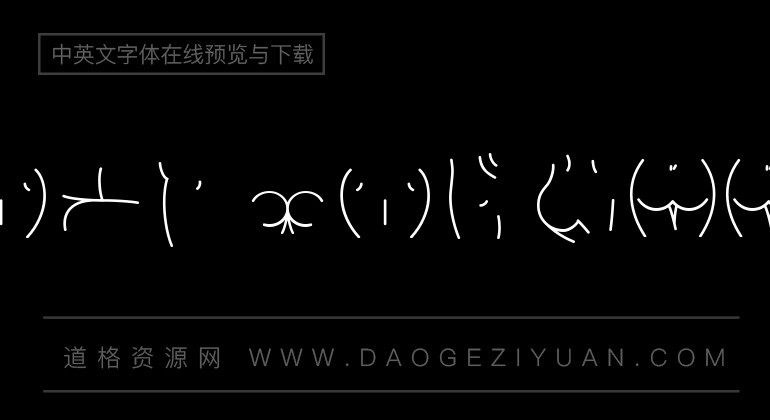
Alphabutt
Alphabutt是一款由字体设计师José Heitor推出的一款免费字体。它是一款具有趣味性和独特性的字体,可以把文本转换为绘画形式,使用它可以增加文本的视觉效果,让文字更加生动有趣。它可以用于各种类型的设计,包括印刷、屏幕、网页等,也可以用在平面设计、礼物包装、杂志封面、标志设计等。
Alphabutt是一款非常不错的手写艺术字体,具有很好的视觉感,适合于文化类的宣传设计、商业类品牌的广告和产品包装设计以及个性化文字排版等较多场景。